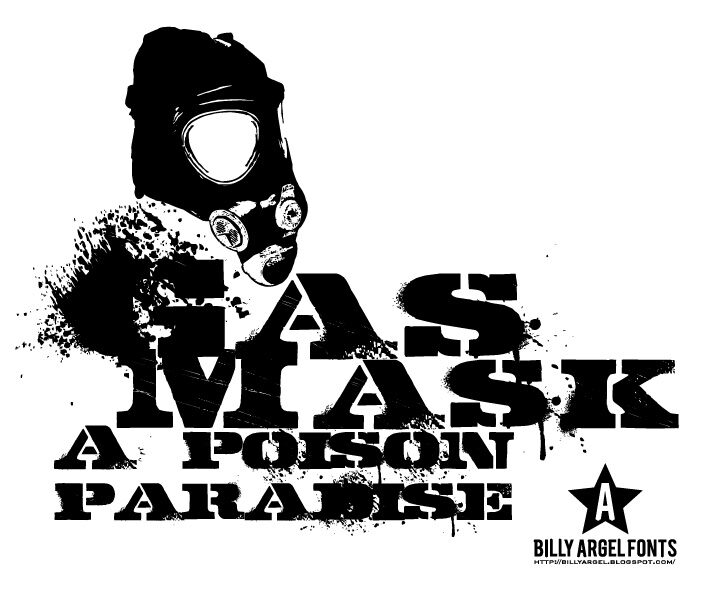
Gasmask von Billy Argel ist eine kostenlose, distresste Military-Stencil-Display-Schrift, die aus breiten, blockigen Versalien und rauen, wie aufgesprüht wirkenden Kanten besteht. Die aufgebrochenen Oberflächen, scharfen dreieckigen Schnitte und die feinen Farbspritzer verleihen den Buchstaben die Optik von Feldbeschriftungen, die durch Beanspruchung und harten Einsatz gezeichnet sind.
Diese abrasive Textur erzeugt einen spannungsgeladenen, improvisierten Look auf Titelseiten von Action-Spielen oder bei taktischen Event-Postern, während die breiten Silhouetten auch auf Album-Covern ihre Wirkung entfalten. Verwenden Sie diese kostenlose Schrift für Streetwear-Designs, Survival-Verpackungen oder Military-Branding, wann immer Sie eine Typografie suchen, die gestempelt, beschädigt und bewusst unbändig wirkt.